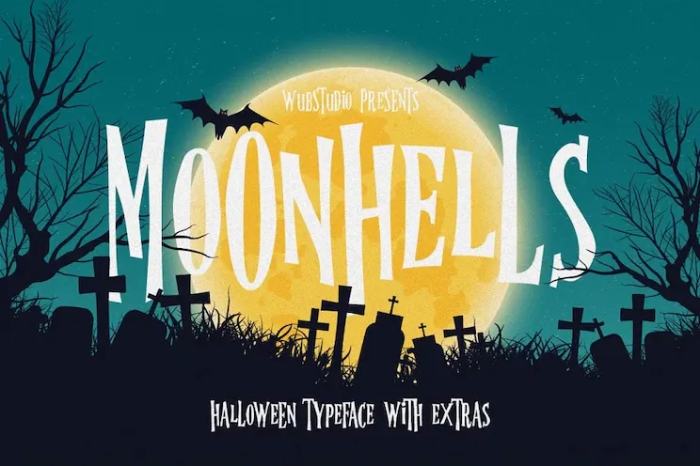
Siete alle prese con la creazione degli inviti per la festa di Halloween? oppure state lavorando su quel progetto a tema pauroso?
Nessun problema perchè questa selezione di fonts pensati per Halloween sono quanto di più prezioso per il vostro invito o lavoro. Una raccolta di 12 fonts da usare per la festa più paurosa dell’anno e non solo.